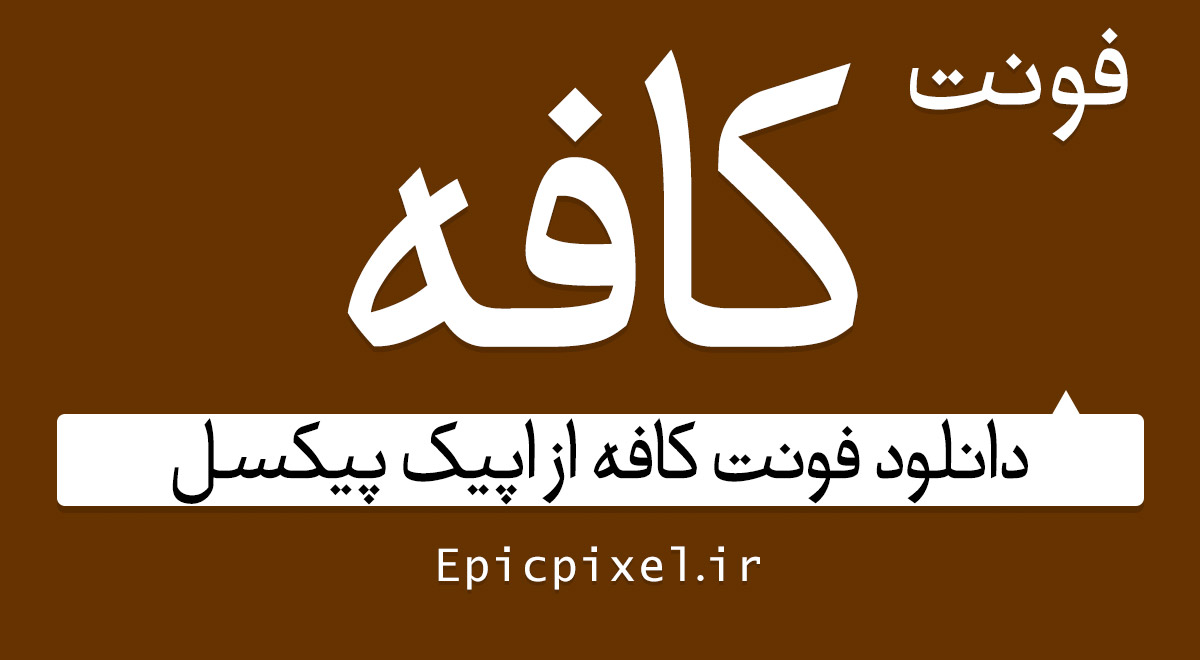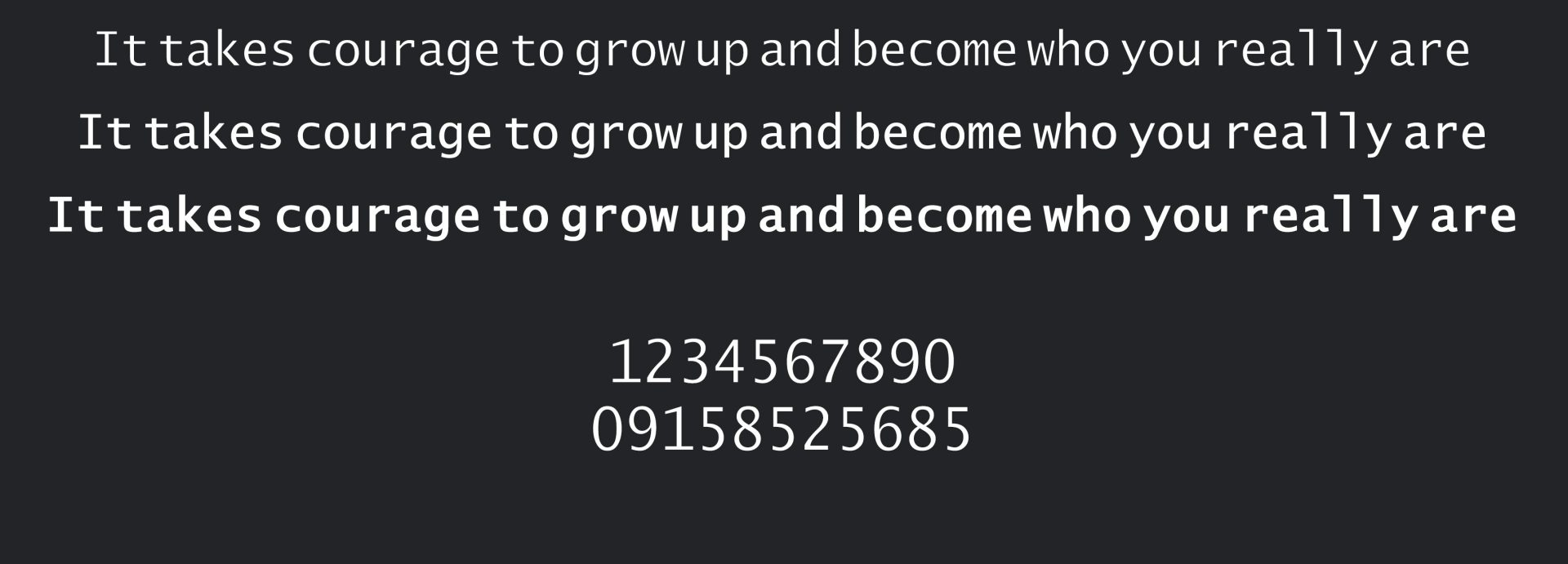
3 فونت کافه فارسی
فونت کافه تجلی زیبایی و ظرافت در صنعت گرافیک
در دنیای گرافیک، فونت ها نقشی اساسی ایفا می کنند. آنها پیام های ما را به مخاطب انتقال می دهند و تأثیر زیادی بر درک و احساسات آنها می گذارند. یکی از فونت های محبوب و پرکاربرد در صنعت گرافیک، فونت کافه می باشد. این فونت با طراحی ظریف و زیبایی خود، حس آرامش و گرمای محیط کافی شاپ را به مخاطب منتقل می کند. در این مقاله به بررسی ویژگی های فونت کافه، کاربردهای آن و نحوه انتخاب فونت مناسب برای پروژه های خود خواهیم پرداخت.
ویژگی های فونت کافه
فونت کافه یک فونت Sans Serif است که دارای خطوط نازک و منحنی های ظریف می باشد. این فونت به خوبی با سبک های طراحی مینیمالیستی و مدرن هماهنگ است. فونت کافه در 3 وزن مختلف موجود است که به شما امکان می دهد تا پیام خود را با شدت های مختلف بیان کنید. همچنین، این فونت شامل کاراکترهای فارسی نیز می باشد که آن را برای استفاده در پروژه های فارسی مناسب می کند.
کاربردهای فونت کافه
فونت کافه برای طیف گسترده ای از پروژه های گرافیکی قابل استفاده است. برخی از کاربردهای اصلی این فونت عبارتند از:
طراحی لوگوها و تایپوگرافی
طراحی بنرها و پوسترها
طراحی وب سایت ها و صفحات فرود
طراحی کارت های دعوت و تبریک
طراحی بسته بندی محصولات غذایی و نوشیدنی
نحوه انتخاب فونت مناسب برای پروژه های خود
دانلودهنگام انتخاب فونت برای پروژه خود، عوامل مختلفی را باید در نظر بگیرید، از جمله سبک طراحی پروژه، پیامی که می خواهید منتقل کنید و مخاطبان هدف خود. فونت کافه برای پروژه هایی که نیاز به حس آرامش و گرما دارند، مانند طراحی لوگو کافی شاپ یا کارت های تبریک، بسیار مناسب است.
سوالات درباره فونت کافه
سوال: آیا فونت کافه فارسی پشتیبانی می کند؟
بله، فونت کافه بصورت اختصاصی برای فارسی طراحی شده و موارد مشابه انگلیسی نیز وجود دارند
سوال: آیا فونت کافه برای طراحی صفحات وب مناسب است؟
بله، فونت کافه برای طراحی صفحات وب بسیار مناسب است، زیرا خوانا و سبک است.
سوال: آیا فونت کافه برای طراحی گرافیک چاپی مناسب است؟
بله، فونت کافه برای طراحی گرافیک چاپی نیز مناسب است، زیرا کیفیت بالایی دارد.
سوال: آیا فونت کافه برای تمام پروژه های گرافیکی مناسب است؟
نه، فونت کافه برای همه پروژه های گرافیکی مناسب نیست. برای پروژه هایی که نیاز به حس رسمی یا قدرتمند دارند، فونت های دیگر مناسب تر هستند.
فونت کافه یک فونت زیبا و کاربردی است که در پروژه های مختلف گرافیکی کاربرد دارد. این فونت به دلیل طراحی ظریف و زیبایی خود، حس آرامش و گرما را به مخاطب منتقل می کند و برای پروژه هایی که نیاز به این حس دارند، بسیار مناسب است. همچنین، این فونت رایگان و شامل کاراکترهای فارسی نیز می باشد.